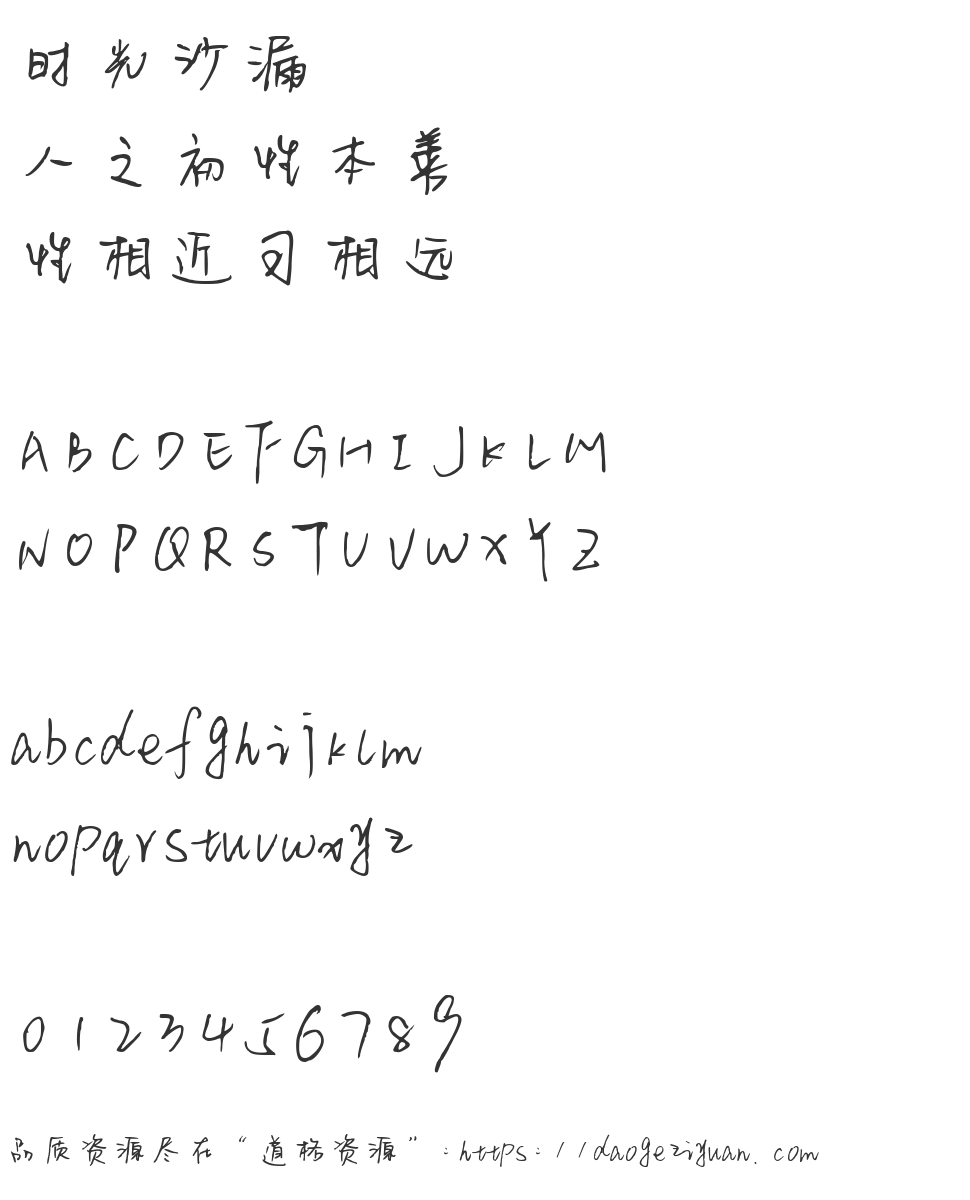
时光沙漏字体是一款见于网络的书法字体,其特点是在字形设计上融合了沙漏的形象,给人一种时光流逝的感觉。这种字体的笔画流畅,线条圆润,同时也富有刚柔并济的韵味。它的字形设计独特,不同于传统的汉字书法,却又具有现代错落有致的美感。在使用上,时光沙漏字体适合于设计一些富有创意和时尚感的文字内容,如广告、海报、漫画等。总之,时光沙漏字体是一款别具一格的字体,深受广大设计师和艺术爱好者的喜爱。内容介绍
时光沙漏是一款非常不错的手写艺术字体,具有很好的视觉感,适合于文化类的宣传设计、商业类品牌的广告和产品包装设计以及个性化文字排版等较多场景。